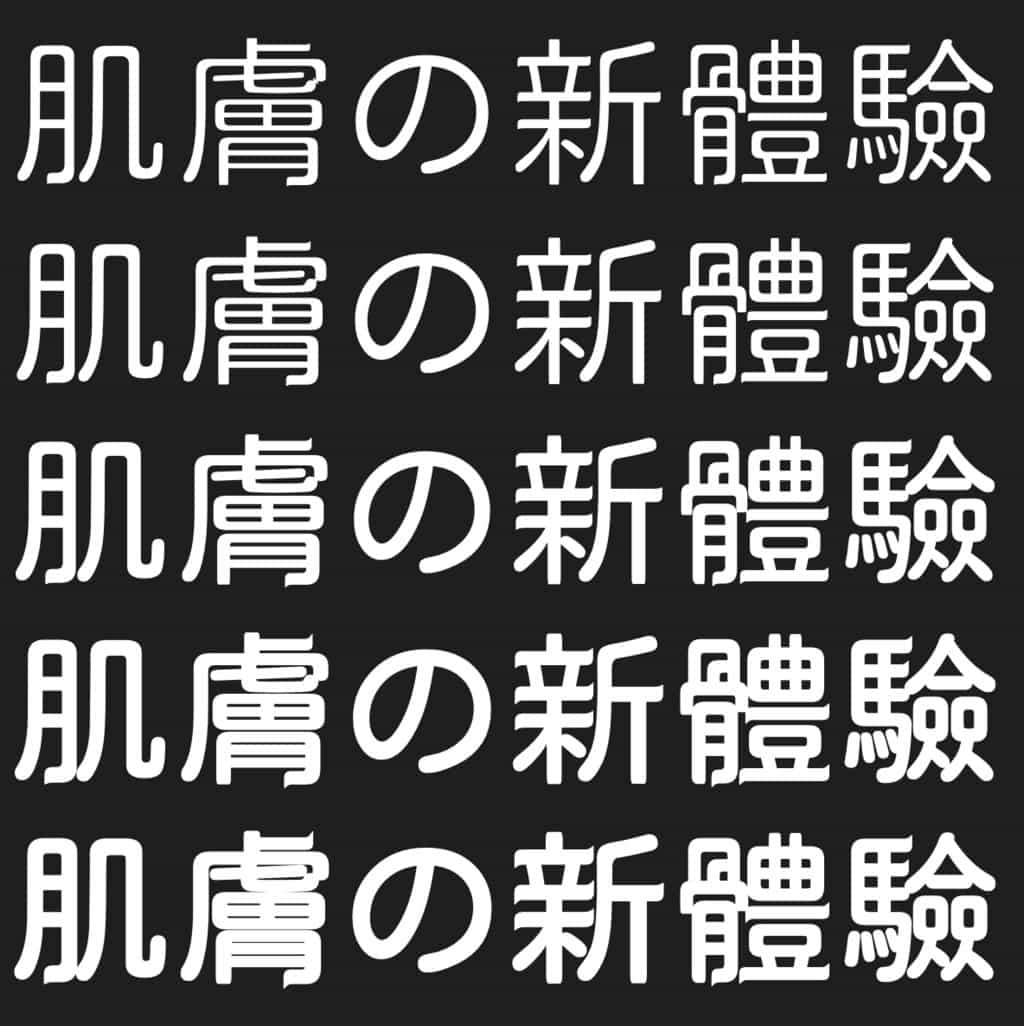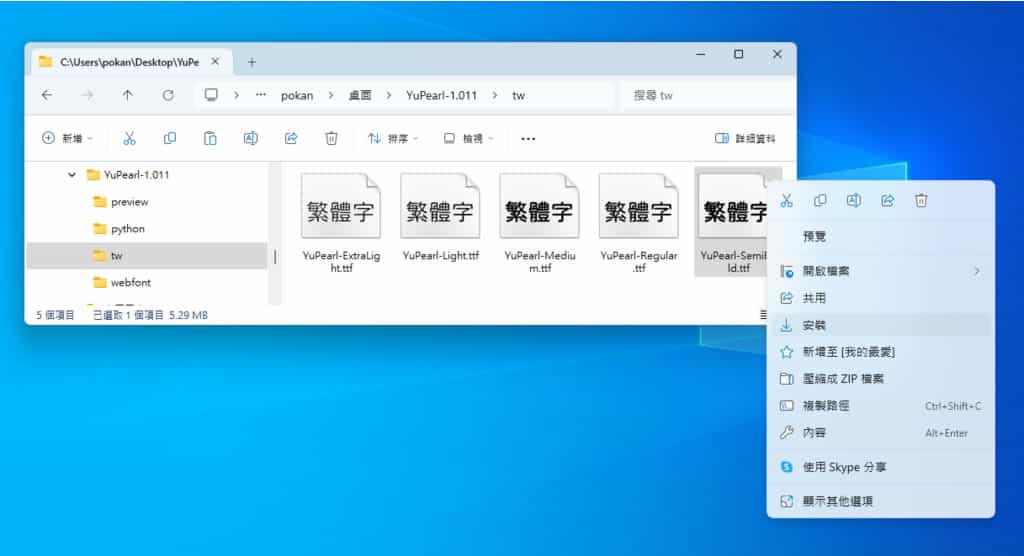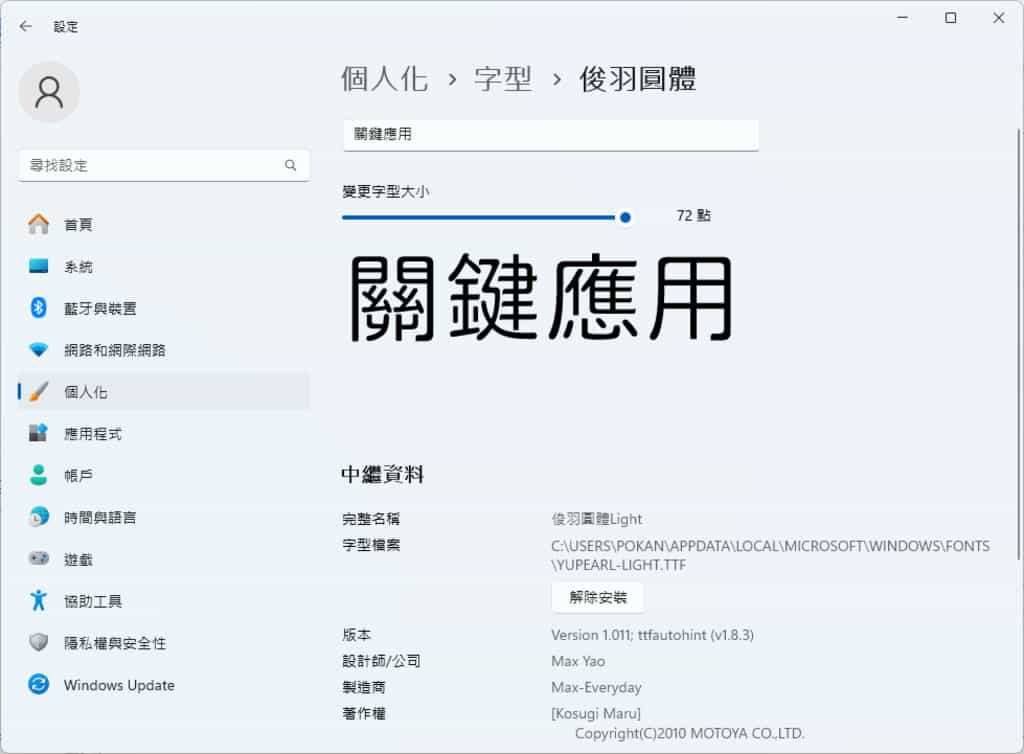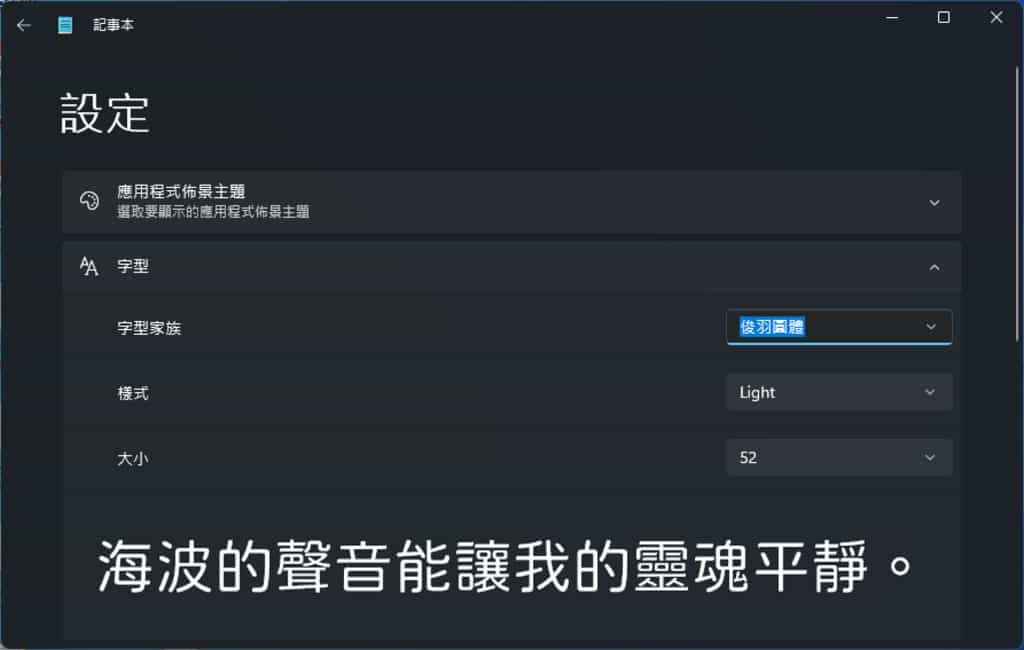
「俊羽圓體」是一套開放原始碼的中文字型,主要是由「JustFont 粉圓字體」改進而來。根據作者的說法,與粉圓體相比,「俊羽圓體」在橫線右上和左下角具有三角形的襯線,並將筆觸由圓頭改為方頭。這套字型提供了 ExtraLight、Light、Regular、Medium 及 SemiBold 五種字重的選擇。採用 SIL Open Font License 1.1 授權條款,